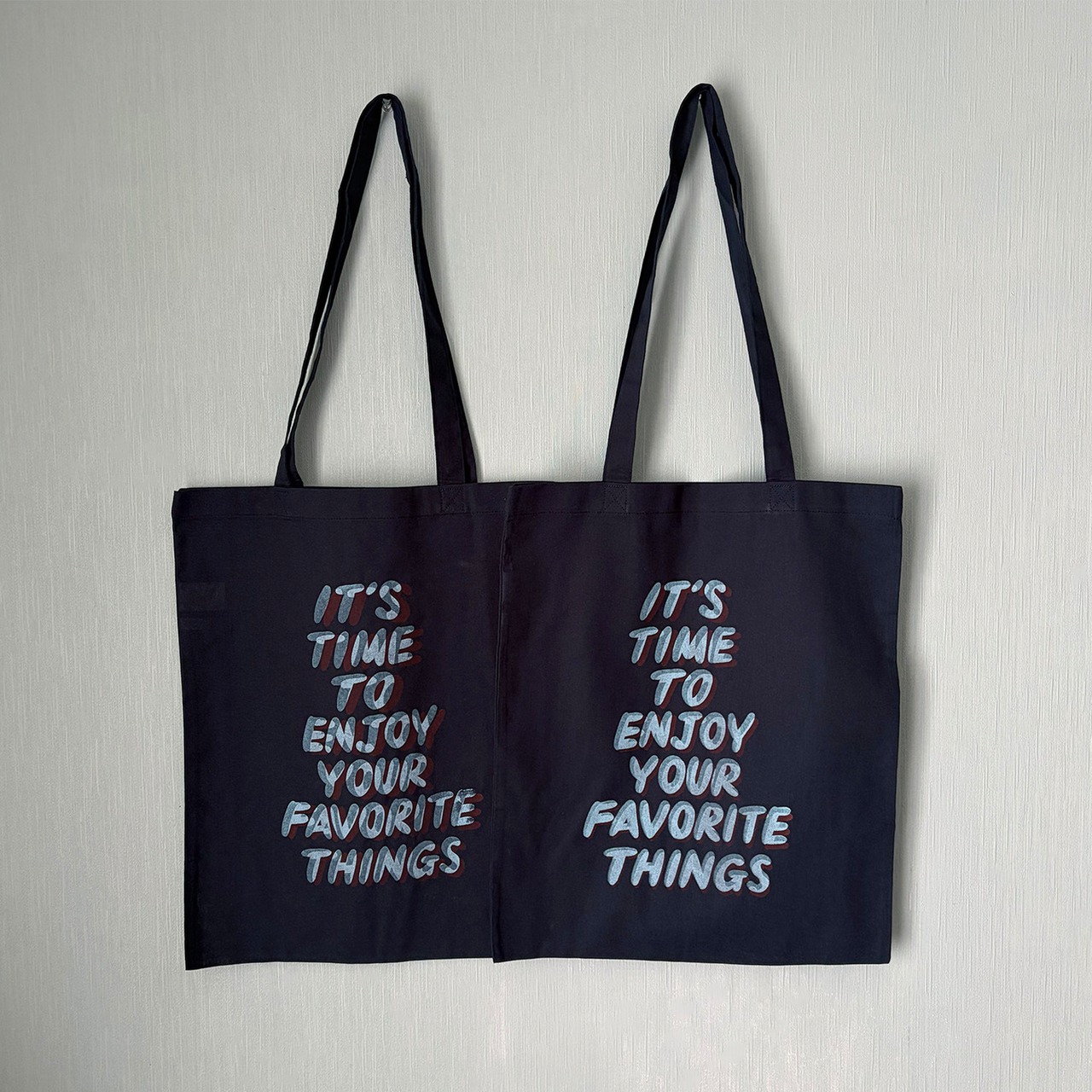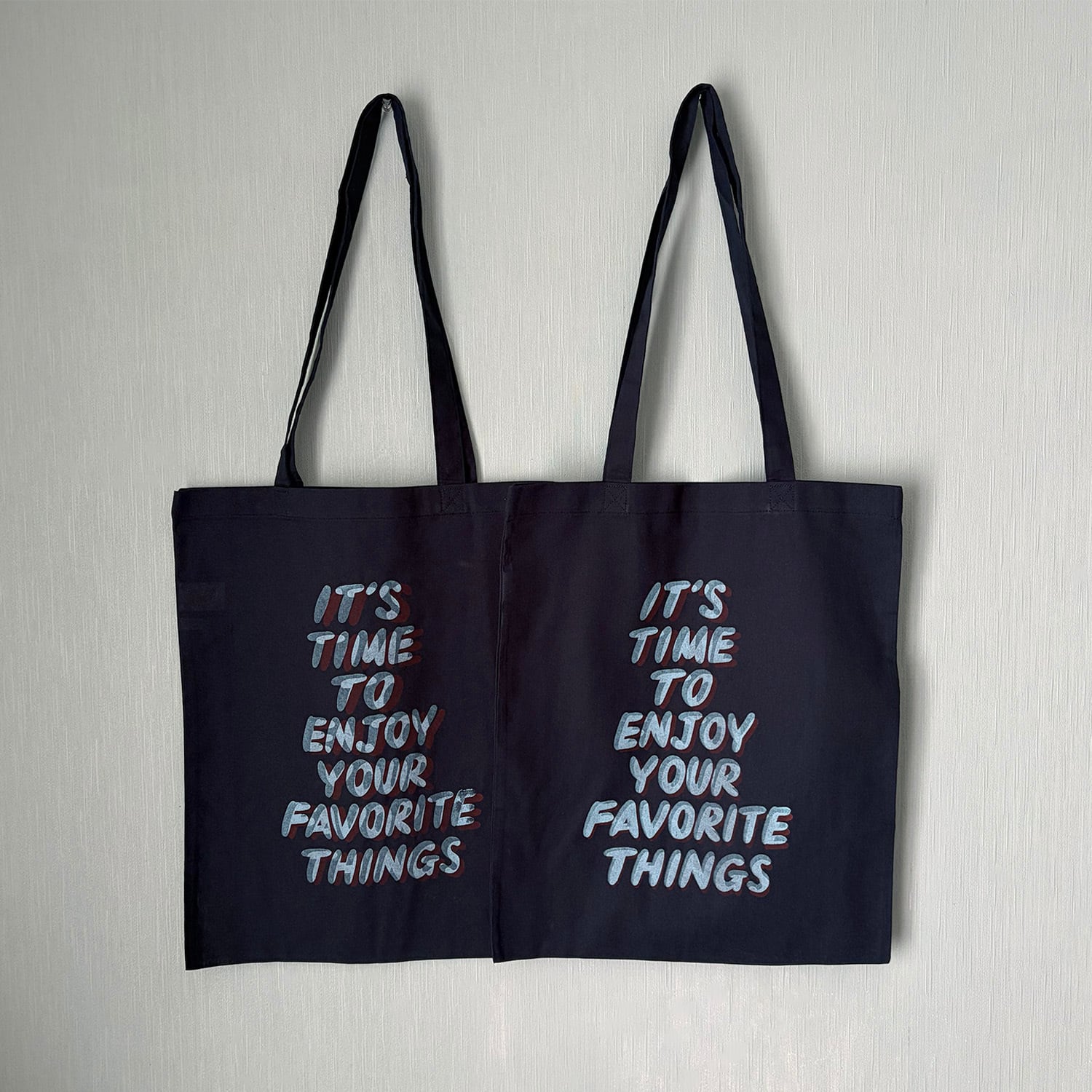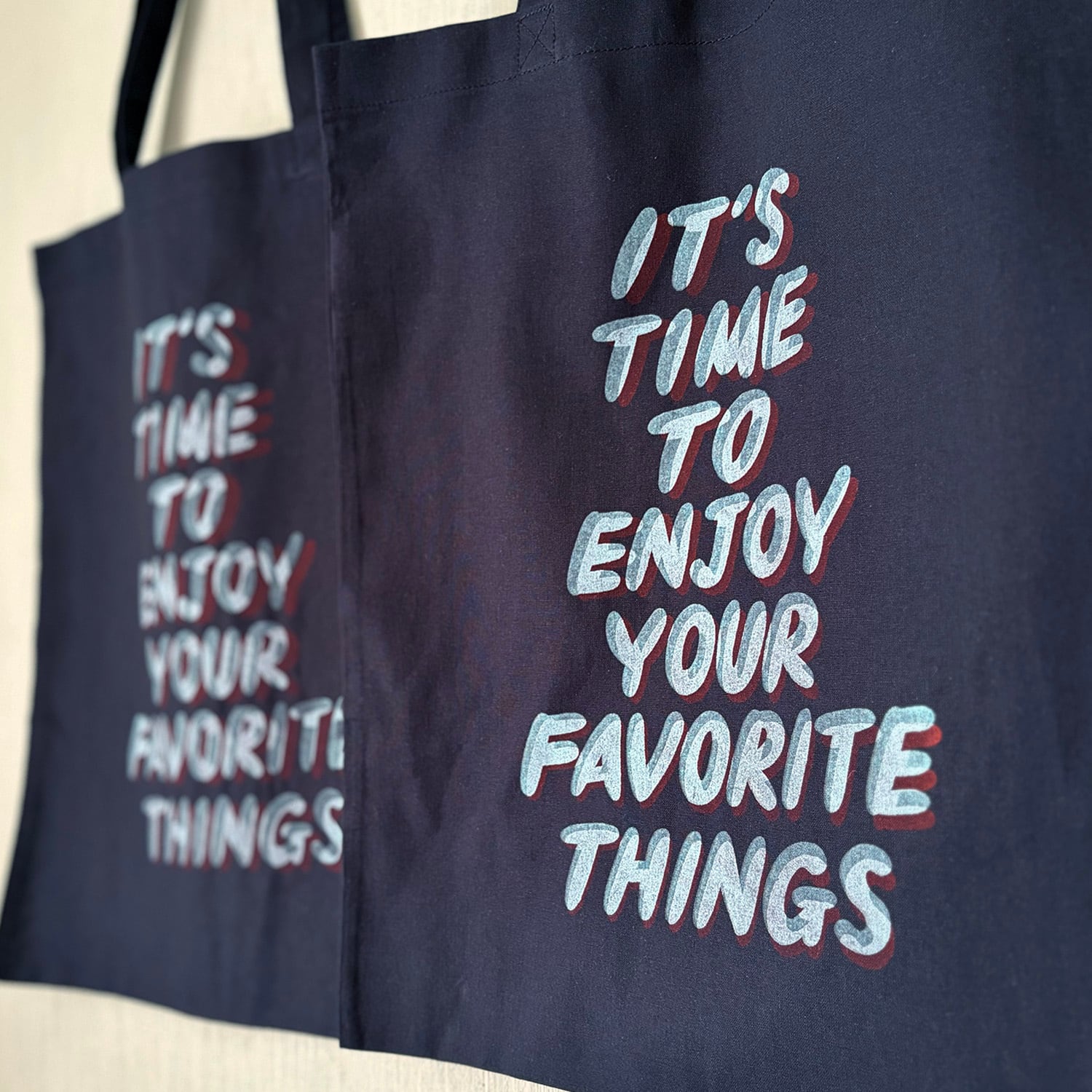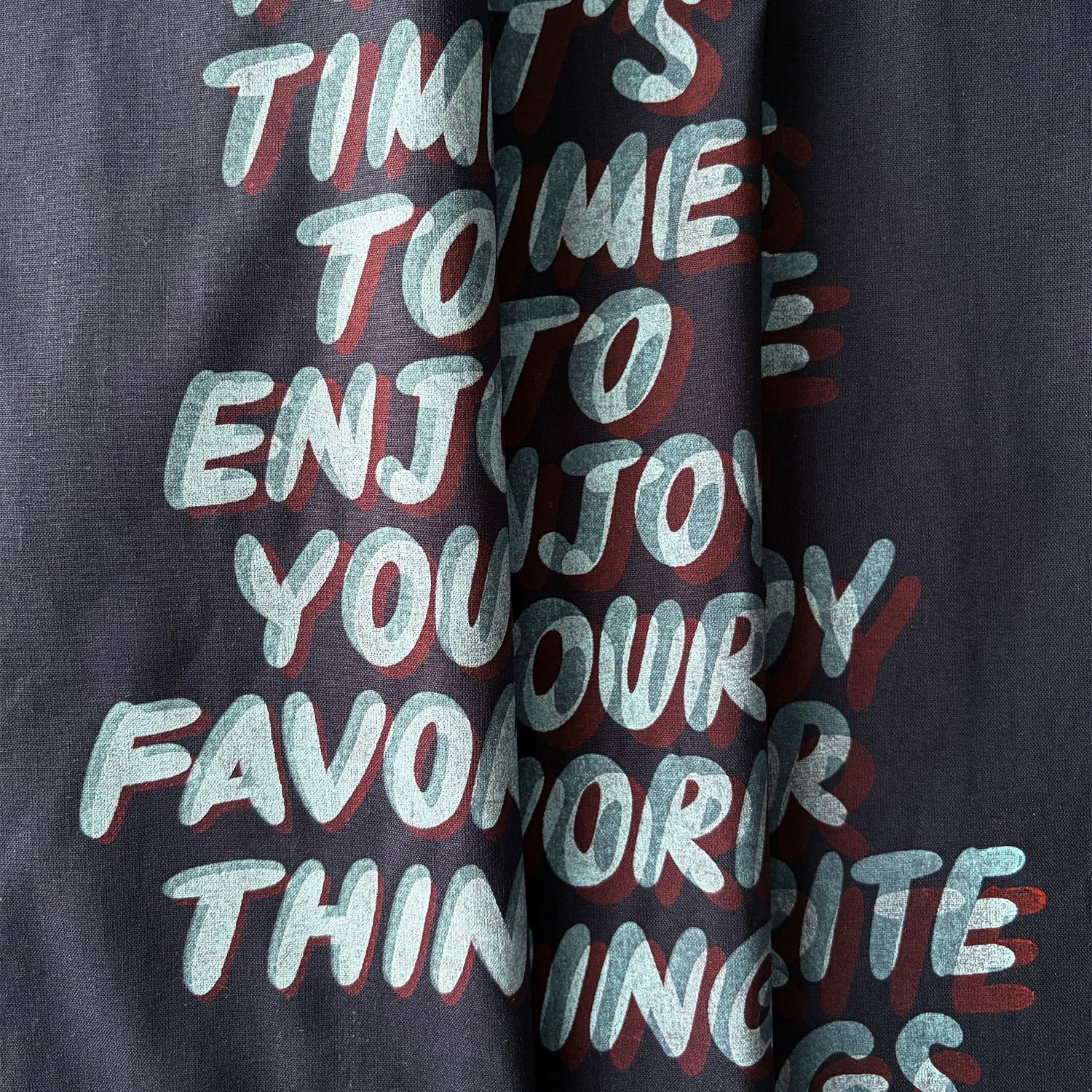
ENJOYトートバッグ(ネイビー)
2025年に販売してから大人気の「ENJOYトートバッグ」
「今こそあなたが好きなことを楽しむ時だよ!」と描いてあります!
水色がはっきり見えたり、模様に見えたり…2色の重なりに個性を感じてください◎
一点ずつシルクスクリーンで手刷りしています(私が!!!)
そのため若干のかすれや重なりのズレがありますが、手刷りの「味」として楽しんでもらえると嬉しいです。